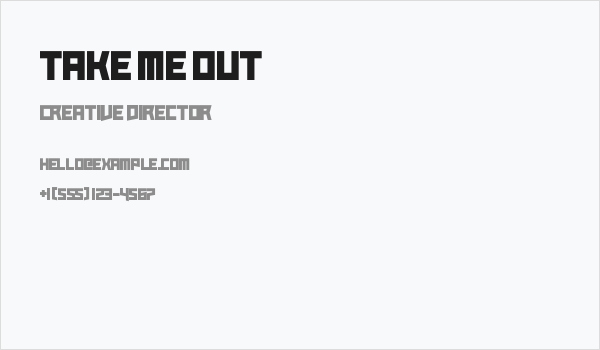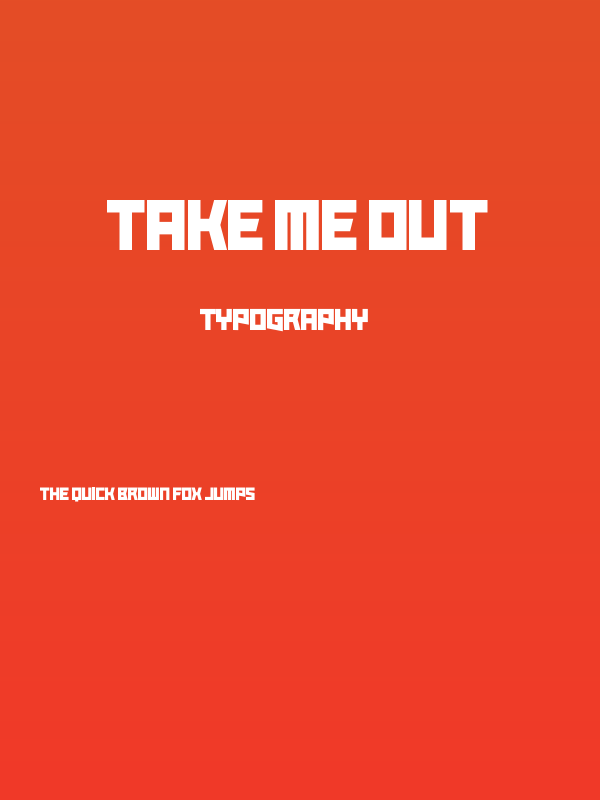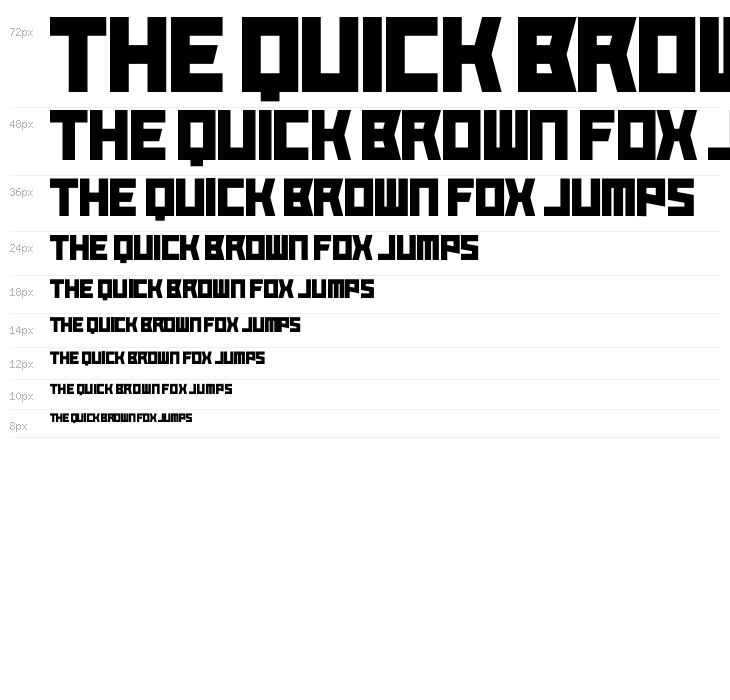
Take Me Out Font
| Progetti proposti | Ideal for posters, logos, video game graphics, and branding materials that require a strong, modern aesthetic. |